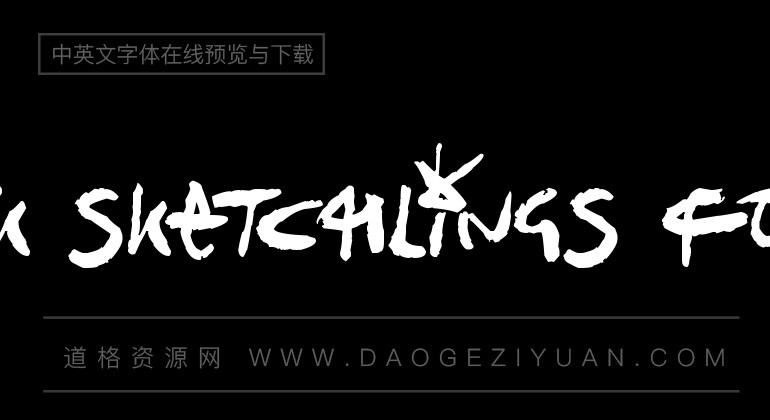
Sick Sketchlings Font 是一种手写风格的字体,它在设计上呈现出非常独特的草图风格。该字体的每个字母都像是一个草图,且线条粗细、曲度和不规则性都有所变化,这使它在设计中非常有用。该字体还包括了一些符号和数字,它们也具有相同的手写风格。Sick Sketchlings Font 可以用于多种设计场景,例如海报、卡片、标志和书籍封面等等。内容介绍
Sick Sketchlings Font是一款非常不错的手写艺术字体,具有很好的视觉感,适合于文化类的宣传设计、商业类品牌的广告和产品包装设计以及个性化文字排版等较多场景。